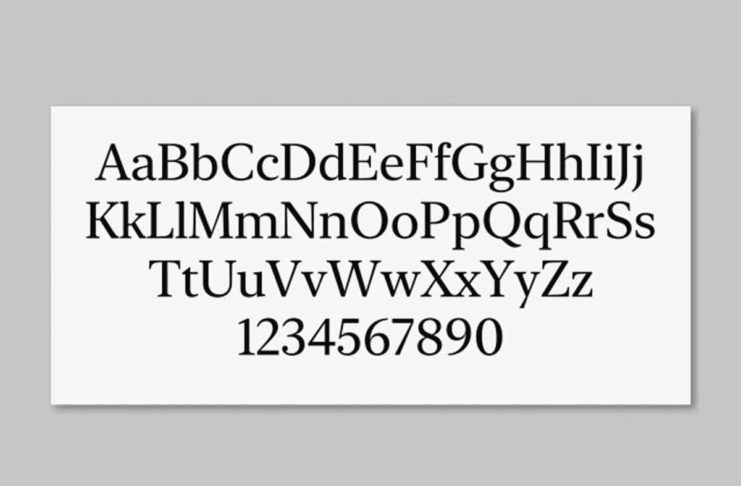
Apple ha rilasciato una versione gratuita e rivista di “New York”, uno dei font inclusi con i primi Mac nel 1984, ideato da Susan Kare – autrice di icone, elementi grafici e caratteri dei primi Macintosh.
In una sezione del sito web dedicato agli sviluppatori, Apple spiega che il nuovo “New York” è un carattere serif basato su aspetti essenziali dello storico carattere, progettato per funzionare bene da solo ma anche insieme al “San Francisco” (il font arrivato con iOS 9 e adottato anche da OS X 10.11 e seguenti come font di sistema). Dallo stesso indirizzo è possiible scaricare gratuitamente il font (un file-immagine DMG con le diverse varianti del carattere); tuttavia, nella licenza d’uso allegata al carattere e alle sue varianti, Apple limita l’utilizzo del suo font alla creazione per mockup di interfacce utente per iOS, macOS, tvOS e watchOS.
Apple in passato ha progettato vari font ma dagli anni ’90 in poi ha lasciato il campo ad altri. Lo sviluppo di “San Francisco” nelle sue varianti e di “New York” è una sorta di ritorno alle origini, quando Susan Kare ideò, tre le altre cose, il carattere di sistema da usare nei titoli, nelle voci di menù, nelle finestre di avviso e dialogo del Mac.
Dopo essersi concentrata su simboli e icone varie del sistema operativo, nel 1983 a designer Susan Kare si concentrò sull’aspetto dei caratteri tipografici. Prima dell’arrivo del Mac sulla maggiorparte dei computer ogni lettera occupava esattamente uno spazio (i font erano a “spaziatura fissa”); il Mac è stato il primo a consentire l’uso di font proporzionali. Bill Atkinson – uno dei maghi dei primi team di Apple che diedero vita al Mac (abbiamo parlato di molti di loro, in questo articolo) – aveva già ideato due font specifici per Mac; la Kare si concentrò sul carattere di sistema (da usare nei menu, nelle finestre di dialogo, negli avvisi, ecc.) e altri caratteri per gli usi più disparati, quelli che in seguito – per volere di Jobs – furono chiamati Chicago, New York, Geneva, San Francisco, ecc.
Steve Jobs era appassionato di calligrafia e nel celebere discorso del 2005 ai neolaureati di Standard, spiegò che i corsi in quetione al Reed College di molti anni prima contribuirono a integrare nel Mac le funzionalità tipografiche che lo resero celebre. Il corso di un monaco trappista (padre Robert Palladino), al Reed College negli anni ’70 ispirò Steve Jobs che cominciò a interessarsi all’arte della scrittura ornamentale, un incontro che si rivelò fondamentale anni dopo quando nacque il primo Mac.